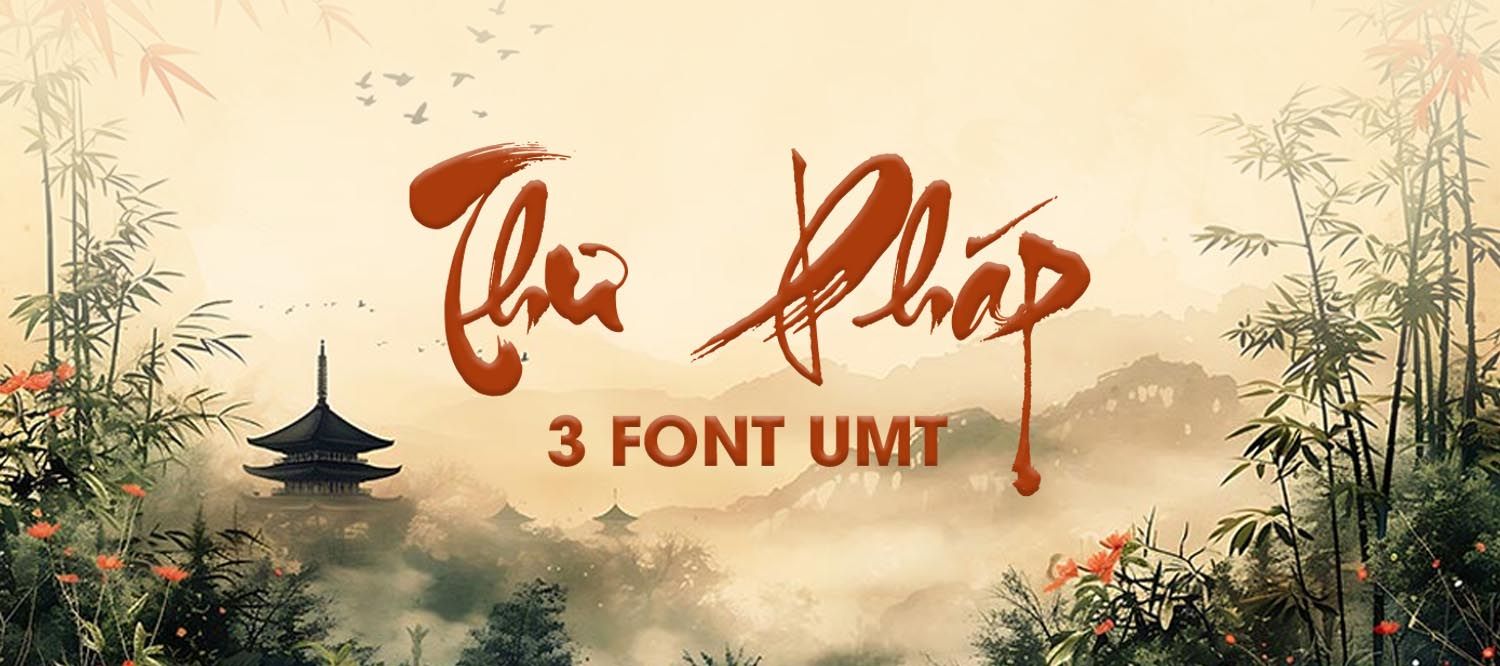
![[Tải Miễn Phí] 3 Font Thư Pháp Việt Hóa UTM Đẹp Nhất 2025](https://cdn.s99.vn//cloud/KNPl96Ytx_qD49p1.jpeg)
Trong thiết kế hiện đại, font chữ không chỉ đóng vai trò thị giác mà còn là phương tiện truyền tải tinh thần và chiều sâu văn hóa. Đặc biệt, với những ấn phẩm mang hơi hướng truyền thống như thiệp Tết, tranh chữ, bao lì xì hay poster lễ hội, việc lựa chọn font thư pháp Việt hóa UTM giúp đảm bảo yếu tố thẩm mỹ đồng thời giữ được bản sắc dân tộc. Trong bài viết này, chúng tôi giới thiệu 3 bộ font thư pháp UTM nổi bật: UTM ThuPhap Thien An, UTM Spring và UTM Azuki – tất cả đều hỗ trợ đầy đủ tiếng Việt và tương thích với hầu hết phần mềm thiết kế như Photoshop, Illustrator, Canva hay PowerPoint.
Font thư pháp Việt hóa UTM là những kiểu chữ mô phỏng nghệ thuật viết tay bằng bút lông hoặc bút sắt, mang đặc trưng thư pháp Á Đông. Được Việt hóa bởi nhóm Urban Type Management (UTM), các font này đã được bổ sung đầy đủ dấu tiếng Việt và được tinh chỉnh để phù hợp với hệ thống chữ quốc ngữ. Không chỉ giữ được phong cách nghệ thuật gốc, font thư pháp UTM còn dễ sử dụng trong môi trường kỹ thuật số, cho phép người dùng ứng dụng linh hoạt vào các thiết kế như poster Tết, câu đối, tranh chữ, thiệp mừng hoặc các sản phẩm truyền thông đậm chất dân gian.
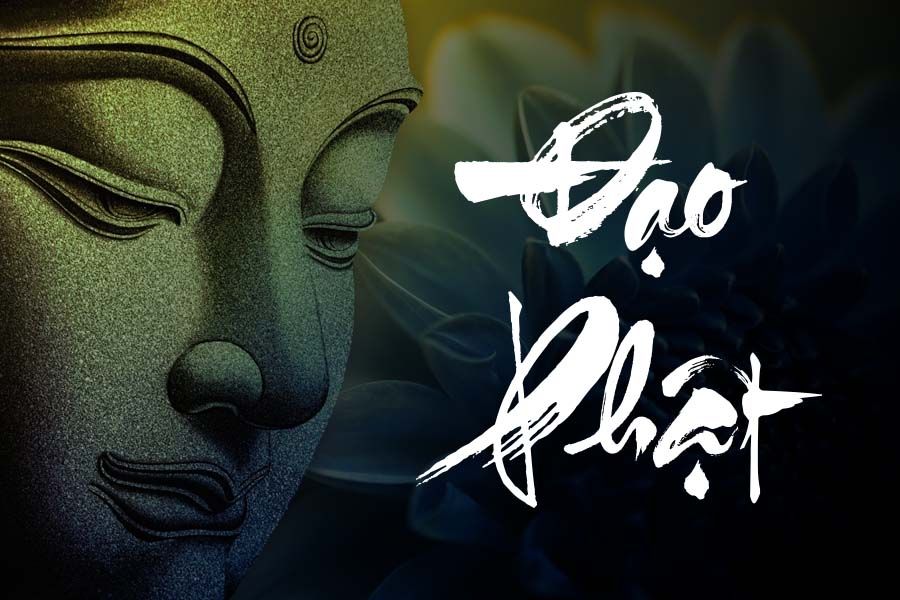
UTM ThuPhap Thien An nổi bật với đường nét mạnh mẽ, dứt khoát và khí chất cổ điển. Nét chữ đậm, đầu nét được nhấn mạnh, phần đuôi bay bổng như được vẽ bằng bút lông thực sự. Toàn bộ phom chữ toát lên vẻ trang nghiêm, linh thiêng – phù hợp với các thiết kế mang tính tôn nghiêm hoặc nghệ thuật thư pháp truyền thống.
Rất phù hợp để trình bày các từ như “Phúc”, “Lộc”, “Tâm”, “Thiện”… Font được sử dụng phổ biến trong tranh thư pháp treo tường, bao lì xì handmade, hoành phi, câu đối, poster Tết, hoặc các thiết kế truyền thông Phật giáo, tâm linh.
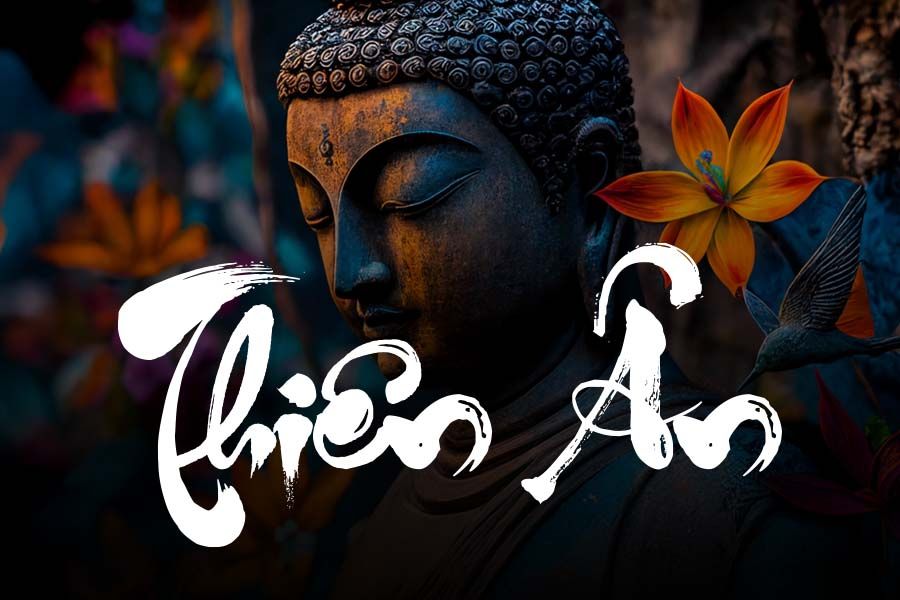
Mang hơi thở mùa xuân đúng như tên gọi, UTM Spring sở hữu đường nét thanh mảnh, có độ nghiêng nhẹ, nét chữ cong mềm và uyển chuyển như cánh đào. Font vừa giữ được chất Á Đông, vừa hiện đại và dễ tiếp cận cho nhiều mục đích sử dụng.
UTM Spring rất lý tưởng cho các sản phẩm như thiệp mừng năm mới, lịch Tết, bảng hiệu spa, poster lễ hội truyền thống, tiêu đề blog cá nhân, hoặc các thiết kế cần sự nhẹ nhàng, nữ tính, sáng tạo.
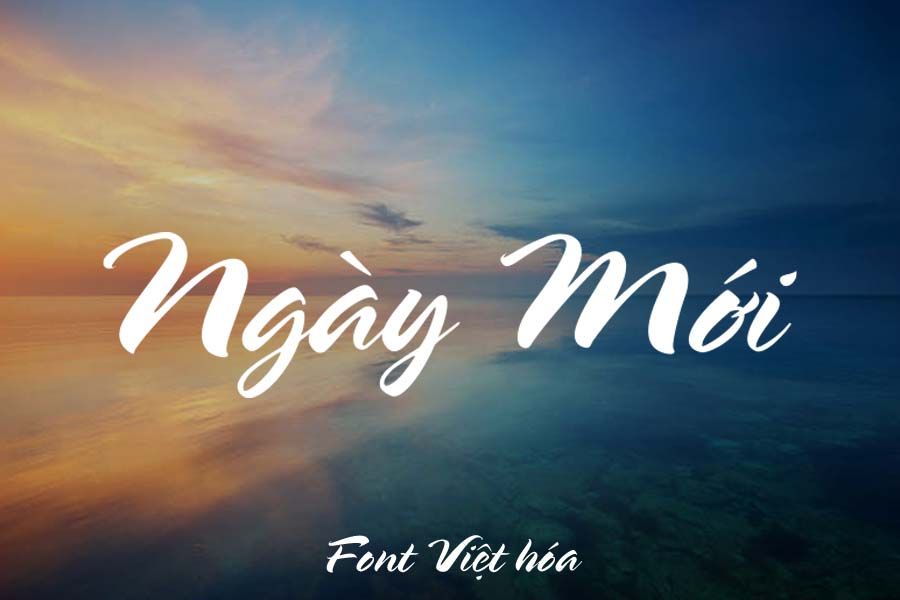
Được lấy cảm hứng từ thư pháp cổ điển Trung – Nhật, UTM Azuki có nét cong mềm mại, độ nghiêng nhẹ và tỷ lệ chữ hài hòa. Kiểu chữ này gợi cảm giác như mực loang trên giấy xuyến chỉ, kết hợp giữa tính cổ kính và hiện đại.
Phù hợp cho các poster triển lãm nghệ thuật, logo nhà hàng Nhật – Hoa, truyện tranh cổ trang, các sản phẩm in ấn theo phong cách Đông Á hoặc thiết kế mang đậm bản sắc văn hóa di sản.
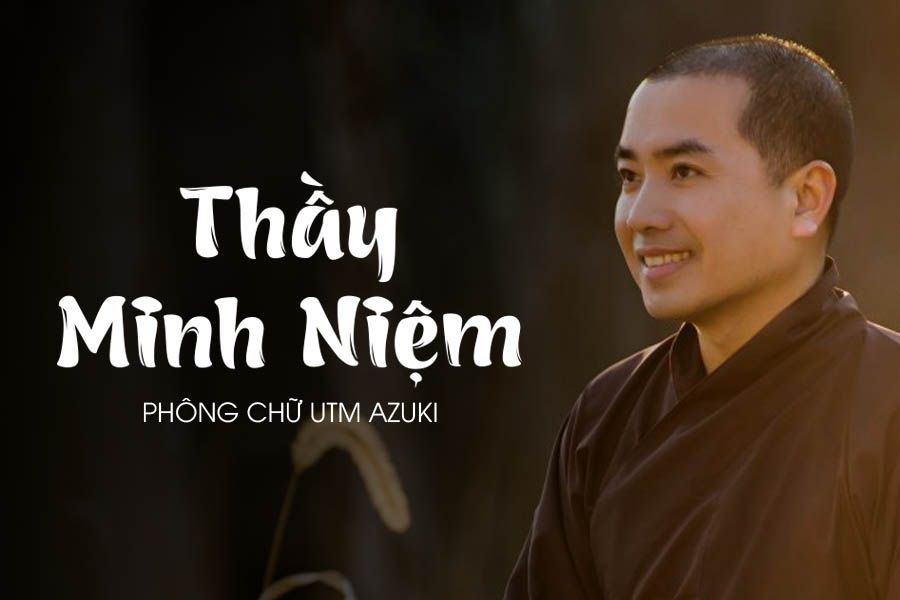
Phong cách: Đậm, dứt khoát, mang nét bút lông truyền thống.
Ứng dụng: Tranh chữ, bao lì xì, poster Tết, hoành phi.
Phù hợp với: Thiết kế Tết, tâm linh, văn hóa cổ truyền.
Phong cách: Thanh mảnh, nghiêng nhẹ, bay bổng.
Ứng dụng: Thiệp xuân, spa, poster lễ hội, blog sáng tạo.
Phù hợp với: Dự án nghệ thuật, thương hiệu nữ tính, mùa xuân.
Phong cách: Cong mềm, hơi nghiêng, đậm chất Á Đông.
Ứng dụng: Logo nhà hàng, truyện cổ, thiết kế văn hóa.
Phù hợp với: Dự án truyền thống, di sản, phong cách Nhật – Trung.
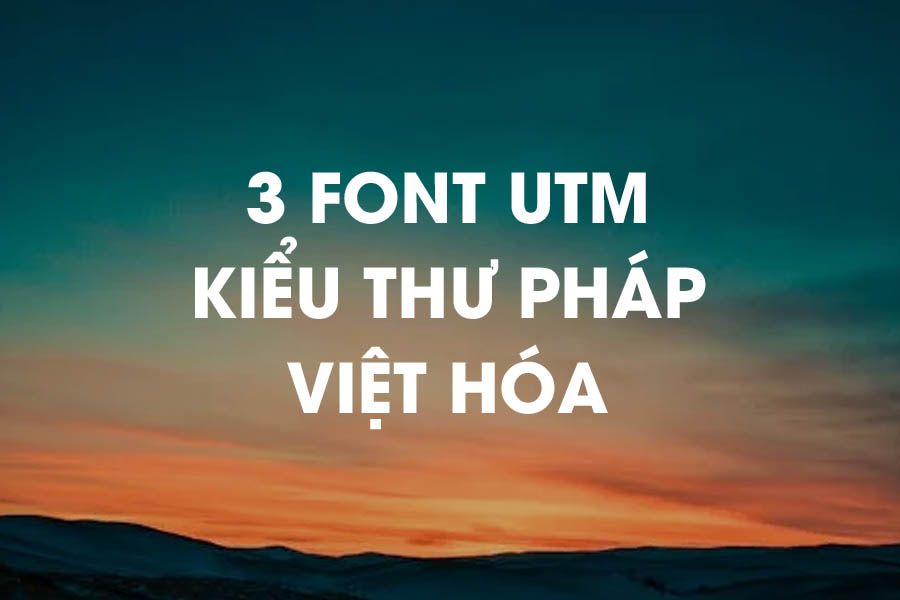
Việc sử dụng font thư pháp Việt hóa UTM là cách hiệu quả để mang văn hóa truyền thống vào thiết kế hiện đại. Mỗi bộ font trong bài viết đều có cá tính riêng: Thien An mạnh mẽ và nghiêm trang, Spring nhẹ nhàng và nghệ thuật, còn Azuki cổ điển và sâu sắc. Tất cả đều hỗ trợ đầy đủ tiếng Việt, dễ dùng, linh hoạt và phù hợp với mọi nhà thiết kế. Hãy tải ngay và sáng tạo nên những tác phẩm mang dấu ấn riêng của bạn.